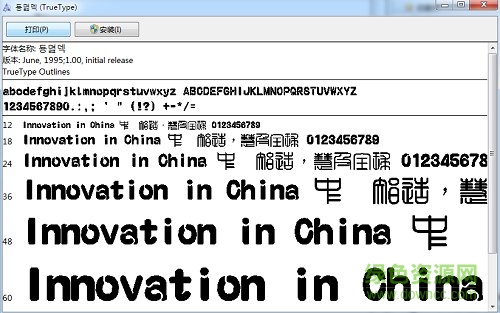
富漢通粗方篆體是一款獨(dú)具特色的電腦字體,根據(jù)春秋戰(zhàn)國(guó)時(shí)期的小篆字體制作而來(lái)的,看上去非常的賞心悅目,個(gè)性十足,有需要用到這款字體的朋友歡迎下載使用!
富漢通粗方篆體是一款根據(jù)古代篆體字體打造的一款中文字體,款字體類似于形象設(shè)計(jì)文字,結(jié)構(gòu)端莊大氣,筆畫細(xì)膩柔美,整體效果非常不錯(cuò),廣泛的應(yīng)用于產(chǎn)品包裝、圖文印刷等行業(yè)!